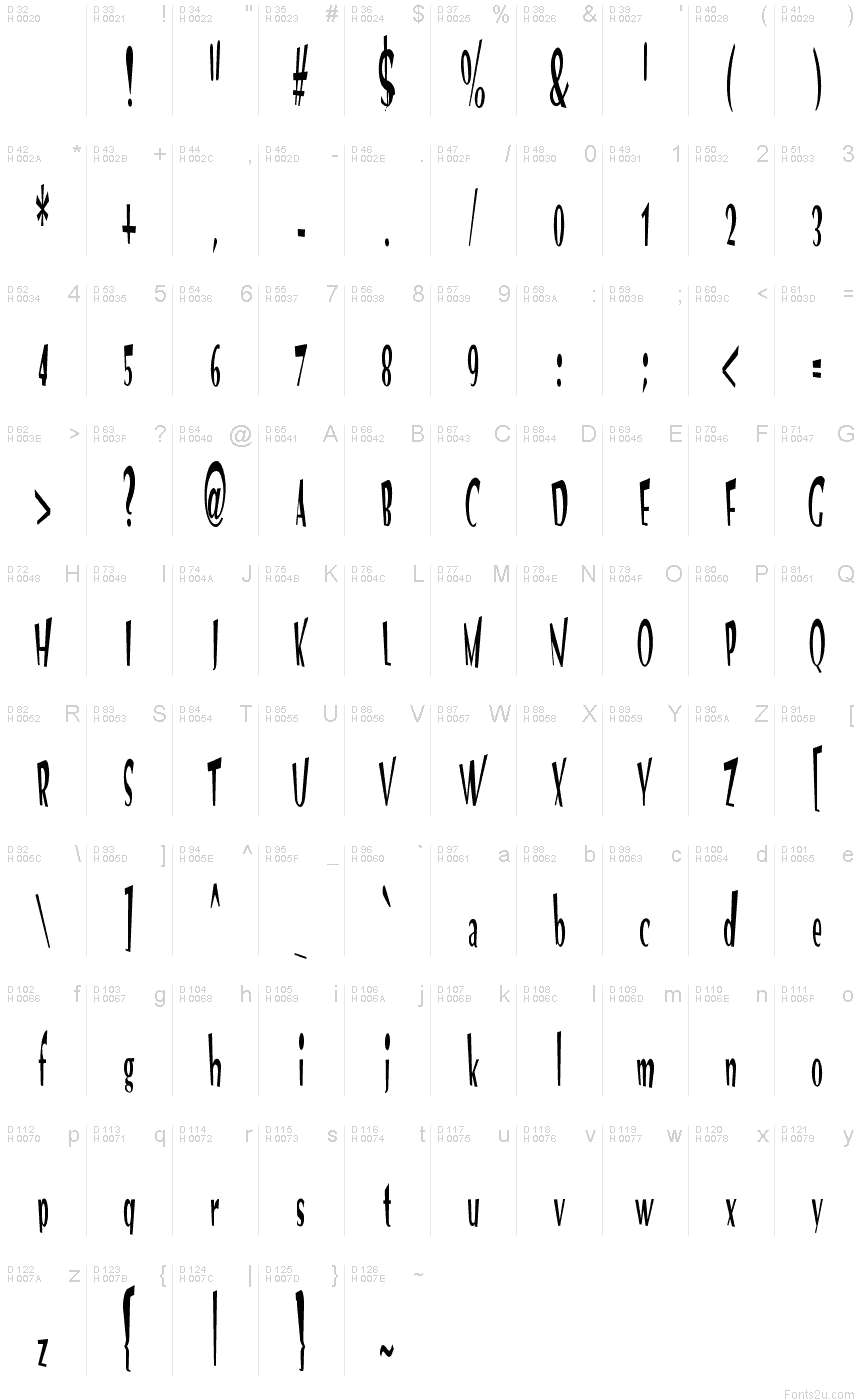
VTC Optika، من V.T.C. Vigilante Typeface Corporation، هو خط عرض مجاني ومشوه يتميز بطابع مضطرب وتأثير بصري ملتوي. الحروف طويلة وضيقة، وتتداخل في منحنيات غير منتظمة وجوانب مائلة، مما يجعل الخط يبدو وكأنه لافتة تمت رؤيتها عبر عدسة منحنية.
هذا يجعله خياراً طبيعياً للملصقات، والمجلات المستقلة، وأغلفة الأسطوانات، وبطاقات العناوين، والعلامات التجارية التجريبية حيث تحتاج النصوص إلى تأثير سريع ومباشر. وباعتباره خطاً مجانياً، فهو مناسب أيضاً لعناوين الأغلفة، ورسومات الفعاليات، وتترات البداية، خاصة عندما تبحث عن إيقاع متوتر وغير تقليدي بدلاً من الخطوط الهندسية النظيفة.